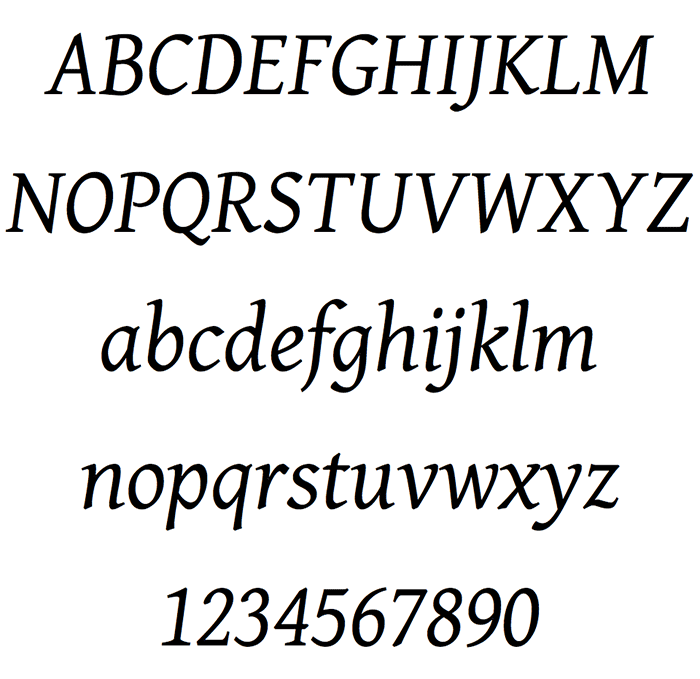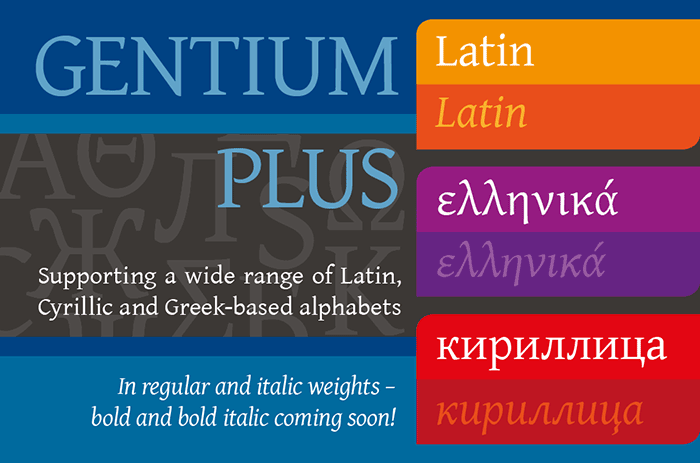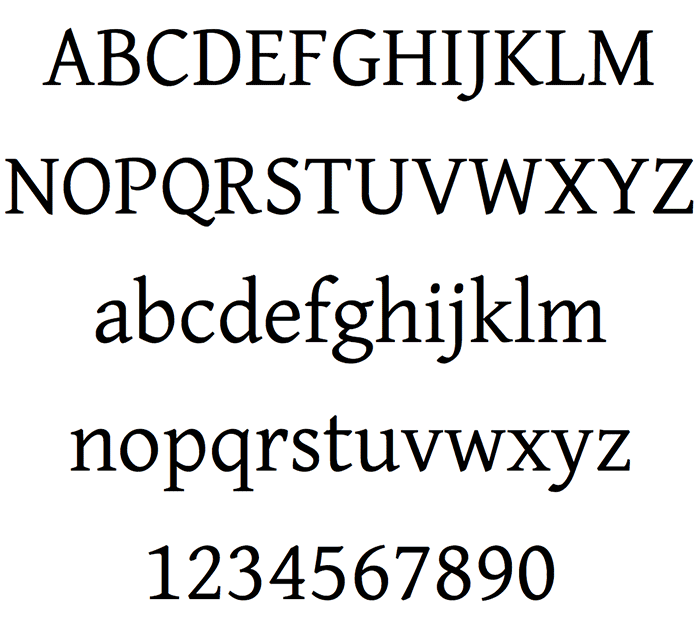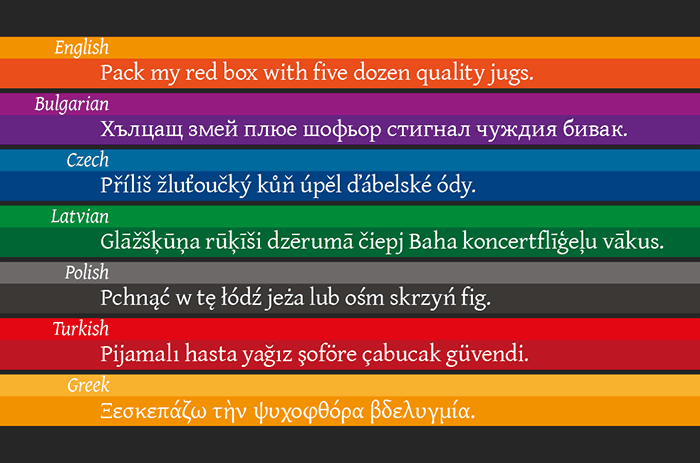
Gentium 6.2
Die Gentium ist eine Open-Source-Schrift von Victor Gaultney. Sie zielt darauf ab, eine möglichst breite Unterstützung lateinischer, griechischer und kyrillischer Zeichen zu bieten.
Da wir die Gentium seit Jahren gerne verwenden (für eine Minderheitensprache) habe ich mal bei SIL nachgesehen und kann bestätigen: Die Gentium ist inzwischen in vier Schriftgraden verfügbar.
Die Stärke liegt sicher in ihrem besonders großen Zeichensatz. Direkt bei SIL.org gibt es mehrere Versionen und auch reichlich mehr Infos.